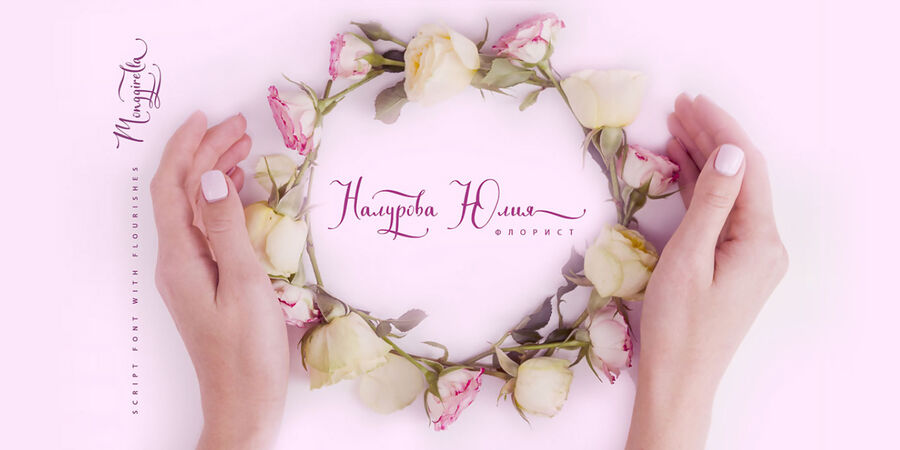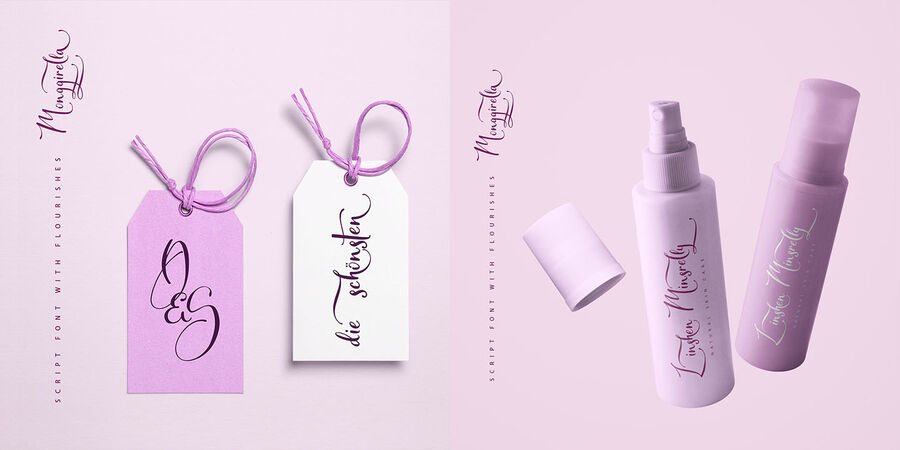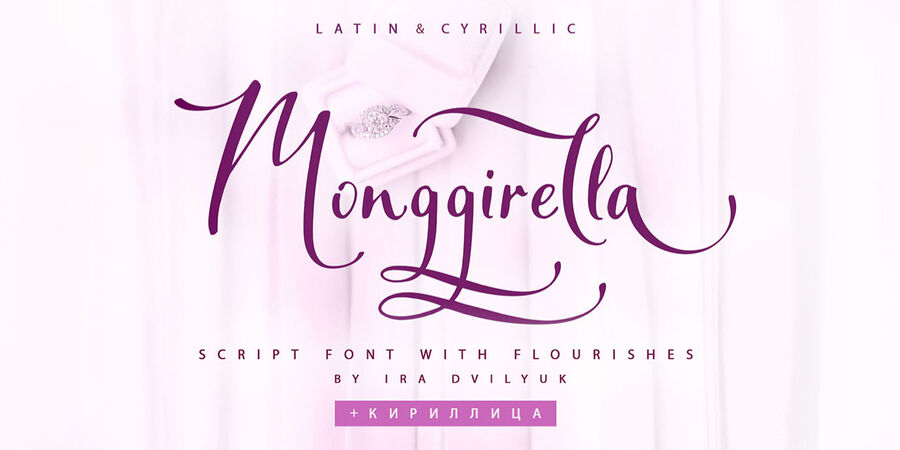
Опис шрифта Monggirella CyrillicРукописний шрифт Monggirella – це каліграфічний курсив із розчерками, який буде чудово виглядати на всіх ваших дизайнах, весільних запрошеннях, любовних листах, матеріалах для брендингу, логотипах, візитівках, цитатах для інстаграму, фешн ескізах, каліграфічних монограмах тощо. Шрифт Monggirella містить повний набір великих і малих літер і може використовуватися для імітації каліграфічних написів. Деякі літери мають розчерки, які ви можете отримати, набираючи числа після букв. Багатомовна підтримка 31 мови на основі латинки та кирилиці.
Шрифт розробила Ірина Двілюк у 2021 році.
Асоціації з сімейством шрифтів Monggirella CyrillicОсобистість і характер гарнітури: